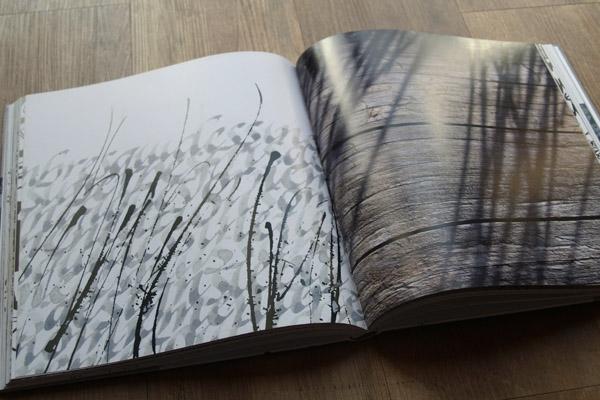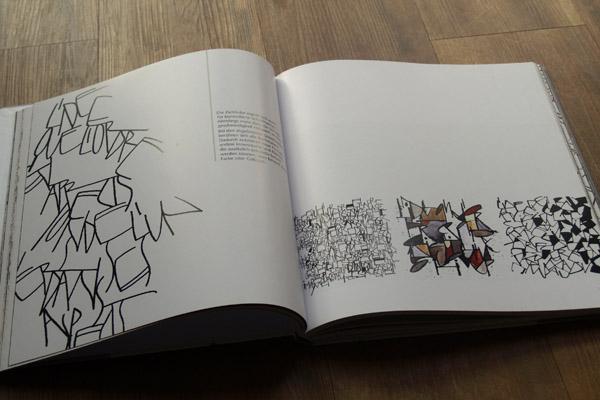
Auf faszinierende Weise setzt die renommierte Schriftkünstlerin Denise Lach fotografische Sujets aus der Natur in Schriftbilder um. Die Natur ist eine überaus reiche, nie versiegende Quelle der Inspiration. Sie lädt uns ein, genau hinzusehen, um unser Auge zu schulen und unsere Beobachtungsgabe zu vertiefen. Beim Gestalten mit Schrift vereinen sich wie bei der Naturbetrachtung das Meditative und das sinnliche Erleben. Wichtiger als die Lesbarkeit der Schrift ist der Autorin dabei die freie schöpferische Umsetzung der Motive in ein eigenes Schriftbild. Die Handschrift bietet allen einen ganz persönlichen Zugang zu Schrifttexturen und deren vielfältigen Gestaltungsmöglichkeiten. Außer Freude und Begeisterung braucht es kaum Vorkenntnisse, um mit verschiedenen Schreibwerkzeugen mit Schrift zu spielen.
›Schriftspiele‹ ist von der Art dem kürzlich erschienenen Band ›Tintentanz‹ sehr ähnlich. Nur, dass hier eine viel klareres Konzept und Thema von der Autorin vorgelegt wird. Es wird zwar auch nicht zu hundert Prozent schlüssig durchgezogen, dafür werden aber vielfältige Vorgehensweisen und Werkzeuge vorgestellt. Auch die gezeigten Arbeiten sind, da von einer professionellen Kalligrafin und keine Studentenarbeiten, qualitativ anspruchsvoller und dennoch inspirierender und wesentlich spannender.
Selbst Schriftanfänger haben sich in einem Workshop an den Arbeiten in diesem Buch probiert und konnten damit mehr anfangen als mit ›Tintentanz‹ – das war auch deutlich an den Ergebnissen zu erkennen.
Hätte ich die Wahl zwischen diesen beiden Büchern, würde ich den vorliegenden Band auf jeden Fall vorziehen. Aber auch ohne diesen Vergleich ist das Werk wirklich eine Empfehlung wert und für jeden, der sich für freie, experimentelle Schrift interessiert – für Anfänger wie Fortgeschrittene – eine Fundgrube an Inspirationen.
Untertitel: Experimentelle Kalligraphie
Autor(en): Denise Lach